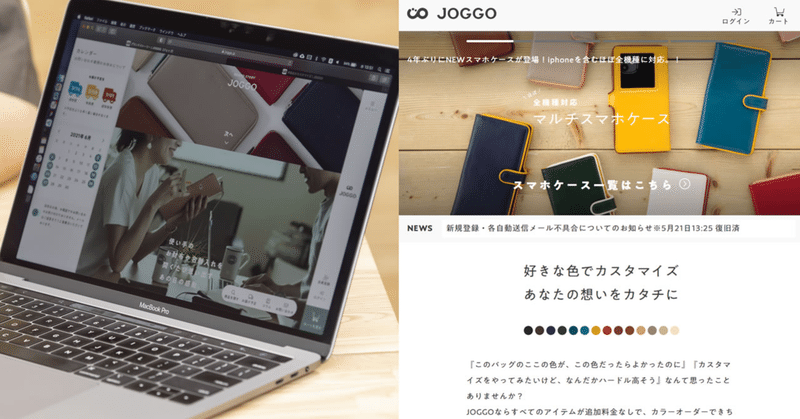
【インタビュー】ECサイトのリブランディングを叶える、A1ゴシックの「伝える力」
実店舗ではないからこそ、そのクオリティーが売上に直結するといっても過言ではないECサイト。ただのお買い物を特別な体験に変えるのは、見やすさや使いやすさといったユーザビリティーだけでなく、商品の背景にある想いを「伝える力」なのかもしれません。
今回は、カスタムオーダー専門のレザーアイテムを販売するジョッゴ株式会社の藤村さんと、ウェブサイト制作を手がける株式会社インプレッシブの喜田さんに、昨年秋に行ったサイトリニューアルの経緯、ソーシャル・ビジネスへの想い、リニューアル後のサイトにA1ゴシックを導入された経緯などをうかがいました。
1.A1ゴシックとは
A1明朝の基本となる骨格を参照して作成された、オールドスタイルのゴシック体ファミリーです。線画の交差部分の墨だまり表現や、エレメントの端々に僅かな角丸処理を加えることで、温もりのあるデザインに仕上げています。 LからBまで4つのウエイトで展開されています。
2.事業は「社会問題を解決するために何ができるか」を考えるところから始まる
―「JOGGO」はどのようなブランドですか。
藤村さん:ブランド名の「JOGGO」はベンガル語で「その人に合った」という意味です。お客様に合わせた商品を提供するというコンセプトから名付けました。いずれの商品も形がスタンダードで誰でも使いやすく、カスタムオーダーができて、かつ手に取りやすい価格帯なのが強みです。
―名入れ刻印もできるそうですね。世界に一つのオリジナルをリーズナブルに手に入れられるのが魅力的です。商品ラインナップを教えていただけますか。
藤村さん:財布やカードケースを中心に、現在は50商品くらい。今後14、5種類の新商品が控えていて、限定色も出る予定です。いまイチオシなのは「革の花」。枯れずにずっと置いておけるので、ギフトで人気です。SNSなどでの反響も大きいですね。
―事業を通して社会問題の解決にも取り組まれているとか。
藤村さん:ボーダレス・ジャパン(※)の事業はすべて、「社会問題を解決するために何ができるか」というところからスタートしています。事業によって問題を解決するのではなく、社会問題から考えよう、と。
ジョッゴは『感動で繋がりを』というビジョンを掲げ、国境、宗教、障害を超えて人々が心で繋がる社会を目指しています。多くの日本人にとっては想像しづらいかもしれませんが、スタッフ達が自分で選択肢を持ち、その上で仕事を誇りと想える状態にしたい。その目指す過程のひとつとして、バングラデシュの雇用を創出するために立ち上げたブランドが「JOGGO」なのです。
※「ソーシャル・ビジネスで世界を変える」ことを目指し、社会起業家が集うプラットフォームカンパニーとして2007年設立。現在、貧困・環境問題など社会問題の壁を超える41の事業を世界15ヶ国で展開中。
―バングラデシュは働く場がなく、経済的に困窮している人たちが多いと聞きます。
藤村さん:「救う」のではなく、一緒に事業をやって利益を生み出すWin-Winの関係を目指していて、行き着いたのが革産業でした。バングラデシュには「イード」というイスラム教の祝祭があり大量の牛肉が消費されるのですが、同時に大量の牛革も発生します。
喜田さん:もともと革産業が盛んではあるけれど、余った革が捨てられ、使われていない現状があって。
藤村さん:そこで革事業を立ち上げ、バングラデシュに自社工場を持つことになったのです。安心して働ける環境を整えるために、最近託児所も開設しました。この1年はコロナの影響もありましたが、幸い現時点で解雇する人もいなくて、なんとか維持している状況です。
工場の前に「雇ってほしい」と人が並ぶため、一人でも多く雇用したいのですが、現状はなかなか難しいです。
―国内にも久米川(東京都東村山市)に工場がありますね。
藤村さん:国内工場として、ジョッゴの超特急便(最短で届ける商品)や、「ENISHI」という国内の革を使った、ハイエンドラインの商品を作っています。
久米川工場UNROOF事業部には、『障害を持っていても自分を信じて輝ける社会へ』というミッションがあります。
多様性(Diversity and Inclusion)を持った方たちが働ける場として立ち上ってはいますが、みなさん障害者雇用の枠ではなく、ジョッゴの1メンバーとしてステップアップを目標に働いています。
キャリアアップや職人としてのスキルを伸ばす環境が整っているので、個々が自発的にどう働きたいかを考えられる職場だと感じています。
3.技術的な問題解決とイメージの統一を目的にウェブサイトをリニューアル
―今回のサイトリニューアルの経緯を教えていただけますか。
藤村さん:僕がジョッゴのウェブサイトに関わるようになった時点で、システム面に手を加えづらい領域が多かったんです。見た目だけは変えたのですが、肝心な商品をカスタマイズするシミュレーターの使い心地が良くなかったこともあり、実際の商品とイメージのずれが生じている状態でした。
このままだと売り上げも見込めないし、なんとしても変えたいと言い続けて、ようやく社内の理解が得られ始めたタイミングでいいパートナーさんに出会えたこともあって、「やりましょう」という流れになったんです。
―喜田さんとの出会いがリニューアルを後押ししたわけですね。お客様の使い勝手をよくするのが一番の目的だったんですか。
藤村さん:安心して商品が買えるECサイトにするのが一番の目的でした。安心の中にはシミュレーターの使い心地も含まれていて、使いやすく、そこで作ったイメージが実際の商品とかけ離れていないこと。それから、カスタムメイドなのでお届けまでにタイムラグがあるのですが、待っている時間も楽しめて、届いたときに幸せを感じられ、次は誰かにギフトとして贈ってみる、という流れを体験できるECサイトにしたいと考えていました。
―以前のウェブサイトはどのような雰囲気だったのですか。
藤村さん:18〜24歳くらいの若い世代にターゲットを絞って、しっかりとそこに寄せていましたね。キャッチーかつポップな色使いで、今とはかなりイメージが違います。
―フォントは何を使っていましたか。
藤村さん:ベースはシステムフォント(予めデバイスにインストールされているフォント)の游ゴシックです。ただ、ユーザーの環境によっては他のフォントに変わってしまう仕組み上の問題があって。
デザイナーとしては、ブランドの雰囲気に合って見た目も全デバイスで統一できるWebフォントを入れたい気持ちもありましたけれど、踏み切れなかった。あまり考えないようにしていたかな……(笑)。
喜田さん:よく言えばポップで、悪く言えば統一感を持たせづらい形で運用していました。そういった問題をリニューアルに合わせて刷新して、ウェブサイト全体の雰囲気もすべてコントロールするというのが目的のひとつでしたね。
―技術的な問題の解決とビジュアルイメージの一新がテーマだったんですね。
藤村さん: LPと広告でそれぞれ異なるターゲットに向けて発信しているものも多かったので、ウェブサイトもSNSもイメージがバラバラで、しっかり統一したいという気持ちがありました。同時にロゴも変えて。
喜田さん:以前はひげのついたセリフ体でしたよね。
藤村さん:太いところと細いところのコントラストがはっきりしていたので、箔が取れやすいという生産上の問題もありました。離れて見ると読みづらい、そういった点がブランド価値を下げているのではとも感じていました。
4.「A1ゴシック」を軸にビジュアルをリブランディング
―そこで、まずはロゴを刷新してリブランディングを図ったわけですね。
藤村さん:ウェブサイトのビジュアルと違和感がないように、A1ゴシックのイメージにマッチするロゴを作りました。
―リニューアル後のウェブサイトで採用されたA1ゴシックには思い入れがあったとか。
藤村さん:僕自身、前からA1ゴシックが好きで、ずっとJOGGOで使いたいと思っていたんです。
―好きになるきっかけはありましたか。
藤村さん:僕の妻がデザイナーでフォントマニアなんですけれど、「A1ゴシック、最近増えてきたね」という会話をよくする程、あちこちで目にするようになって。もともと刻印や孔版印刷のようなレトロ系の印刷が好きだったこともあり、気に入っていたんです。そのうち、見れば見るほど「ジョッゴに合っているんじゃないか」と思うようになりました。。
喜田さん:にじみの感じがエンボスにしたときの刻印に似ていて、革商品との相性がすごくいいですよね。
藤村さん:リニューアル前はロゴとも合っていないし、イメージがさらにバラバラになるだけだったので、使いたくても使えない状況にありました。
喜田さん:フォントだけ先行して変えてもあまり意味がない。ブランディングという大きなくくりの中でフォントを統一していかないと良いものにはなりませんからね。ですので、リニューアルのタイミングでA1ゴシックに変えるよう、かなり説得しましたよね。
藤村さん:「なぜいいのか」ってところをね(笑)。
カジュアルさは保ちながらも、商品のよさをきちんと伝えるビジュアルにするために、A1ゴシックが持つ整った感じやふところ感、アキ感がぴったりだと思ったんです。
―社内プレゼンをされたのですね。反応はいかがでしたか。
藤村さん:「フォントを変えて、実際どう影響するの?」という反応だったので、これはもう見てもらうしかないと。ビジョンを一枚絵のビジュアルにして、先行して作ったロゴと一緒に見せて説得しました。ビジョンというのは、僕たちがどのような想いでお客様に商品を届けたいかをまとめたものです。伝えたいメッセージとフォントが合っている、これってすごいことだと思うんですよね。「どうですか、やりましょうよ、進めていいですか」と、喜田さんにも一緒に説得してもらいました(笑)。
社内を説得する際に用意した資料をベースに作成したJOGGOのブランドストーリーのWebページ。ビジュアルとともに想いを伝えるメッセージはA1ゴシックのWebフォントで表示されている。
5.モリサワWebフォントの魅力
―お二人の熱意と苦労の上に実現したものだったんですね!ところで今回、モリサワのWebフォントを導入するにあたって気になる点はありましたか。
喜田さん:ローディング時間ですね。日本語は漢字・ひらがな・カタカナと文字数がとても多いので、フォントの読み込みでユーザーを待たせてしまうかもしれないというのが一番のボトルネックで。ウェブの世界は読み込みが遅いとユーザーが離れていくため、ストレスを与える表示速度にならないかが一番の懸念点でした。
藤村さん:Webフォント自体は以前から、グラフィカルなフォントを使いたいとき、画像をいちいち作り直す手間を減らすために使っていました。ただ読み込みの問題もあるので、あくまで部分的でしたね。
喜田さん:今回、ウェブサイト全体でモリサワさんのWebフォントを導入してみて、読み込みは気になりませんでした。ローディング時間によってユーザーが離脱するケースも現状ないので、そういう意味でもよかったなと。
喜田さん:フォントはブランディングする上で不可欠で、より直感的に伝わるツールだと思うんです。印象って文字だけではなく、全体の雰囲気で伝えるものだから、きちんと伝わればブランドユーザーのロイヤリティー、「好き」という気持ちがどんどん高まっていく。
ウェブサイトって一番ユーザーと近いインターフェースなんですよ。そのすみずみまで自分たちの意思をほどこせるのだから、ブランディングにWebフォントを使わない手はないですよね。
藤村さん:フォントに触れている時間って、実は人生の中の大半を占めているのに、一般的には「そのへんにあるもの」としか認知されていないんです。
ウェブサイトの文字は、その向こうにいるお客様との会話だと思う。だから、気持ちに寄り添ったフォントを使うと、ウェブサイトの質がぐっと上がるはずです。
喜田さん:いまお話ししたとおり、フォントはとても優秀なブランディングツールなんですが、日本語フォントの場合、導入のしづらさがハードルになっているケースが少なくない。その点モリサワさんのWebフォントはそこを解決してくれているので、みなさんにもぜひ使っていただきたいです!